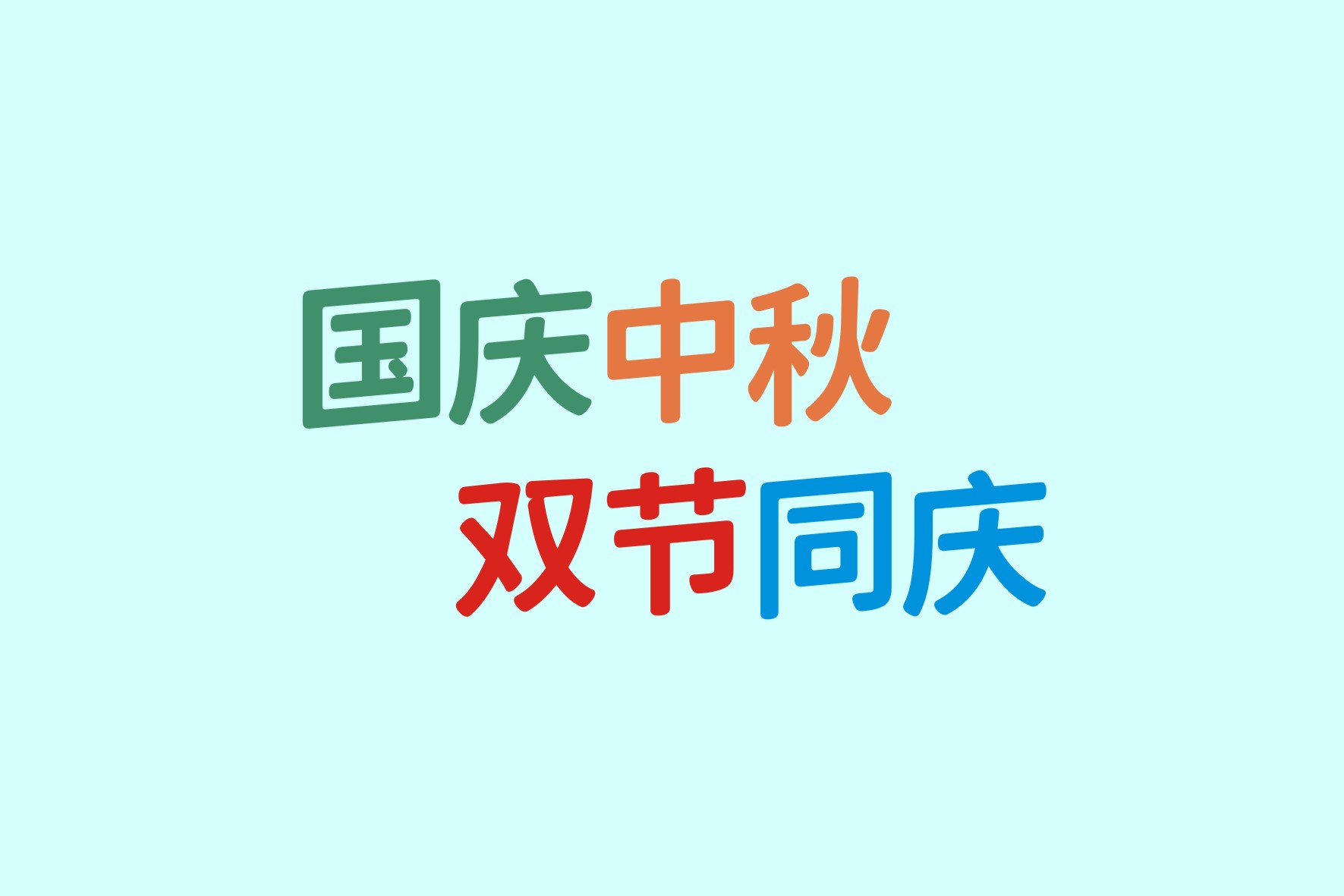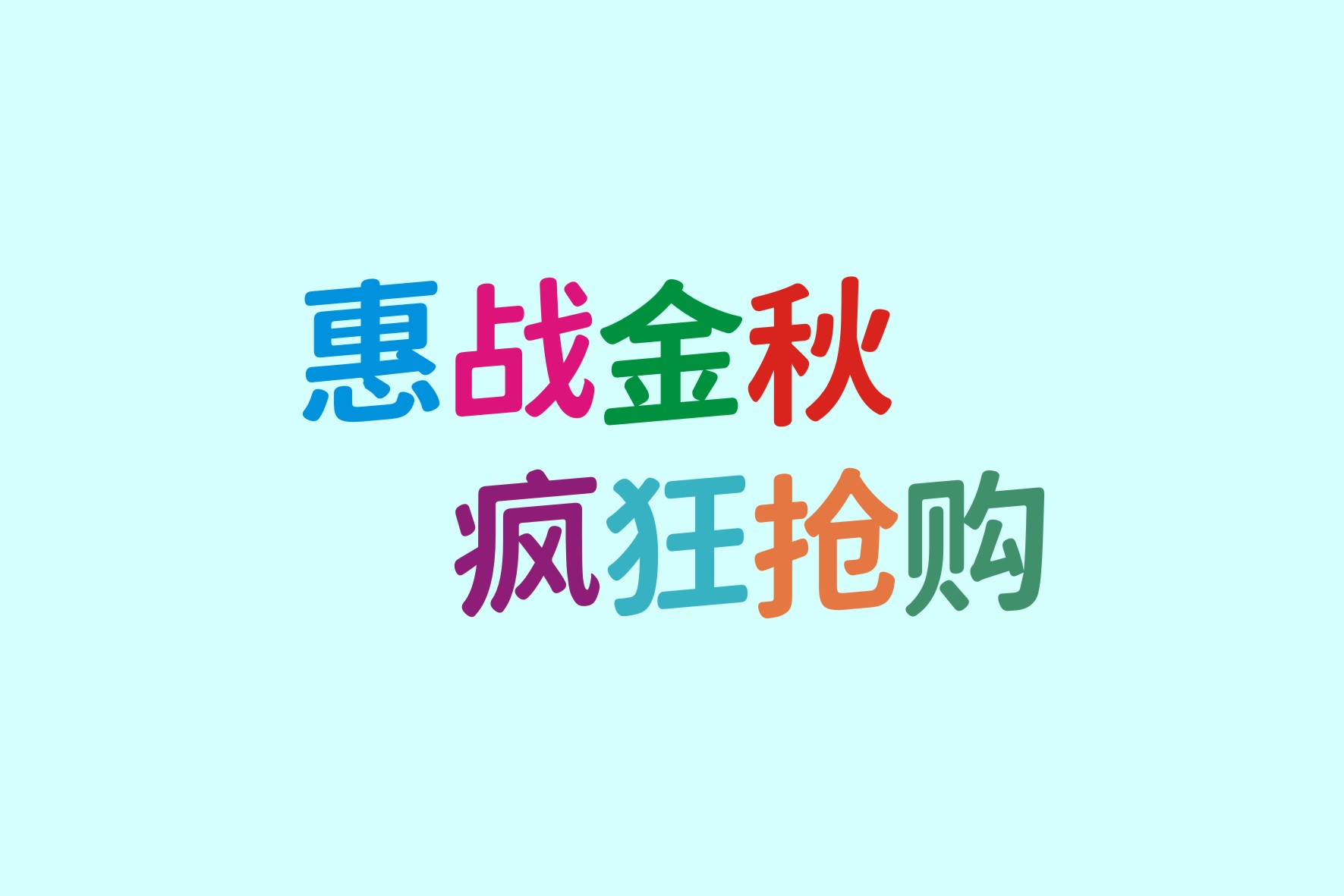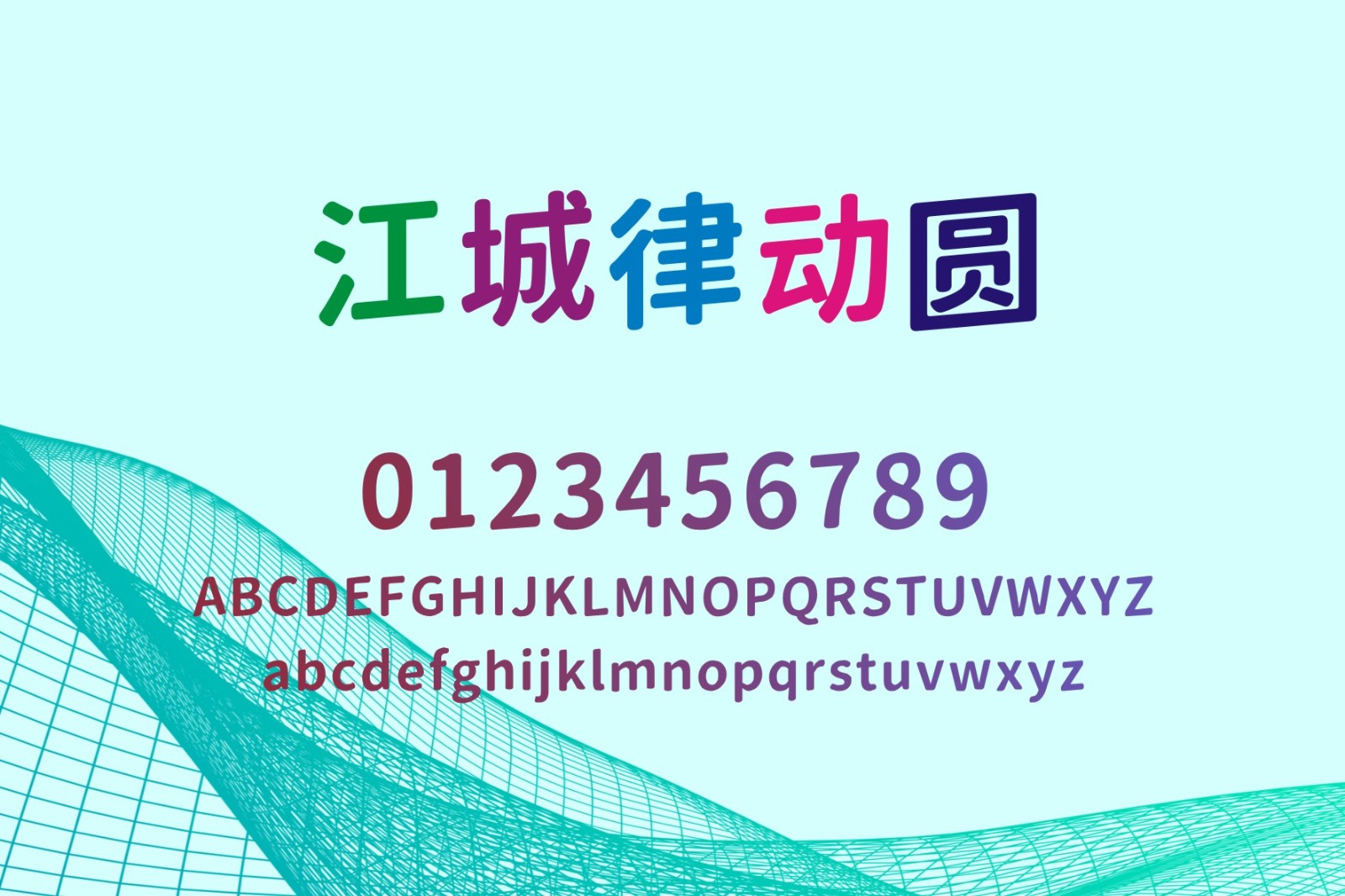
字体名称: 江城律动圆
江城律动圆
江城律动圆介绍
基于狮尾圆体SC-Bold向上倾斜5度改造,字体向上倾斜,上下律动,自带活动促销BGM,天生适用于活动、促销等广告语,适当缩小字间距效果更佳哦。
江城律动圆字体JiangChengLvDongYuan字库是一款让人赏心悦目、百看不厌的中文字体,适合各类广告和产品包装设计应用,字体大小15.98MB,格式为ttf字体,上传用户是青柠檬,作者/版权方为刘鹏